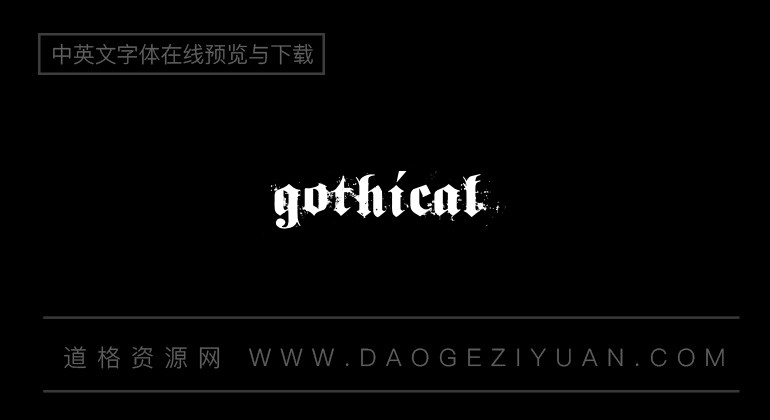
Gothical 字体是一款由英国设计师 Paul Lloyd 创作的哥特式风格字体。它通过结合传统的哥特式风格和新的现代元素,创造出一种新的字体风格。Gothical 字体的特点是它的字母笔画比较厚实,拉长的笔画非常突出,使用该字体的文字显得更加有力,更有层次感。它适用于多种场景,比如海报、书籍、网页等,可以给作品带来一种古典而又充满活力的感觉。内容介绍
Gothical是一款非常不错的手写艺术字体,具有很好的视觉感,适合于文化类的宣传设计、商业类品牌的广告和产品包装设计以及个性化文字排版等较多场景。